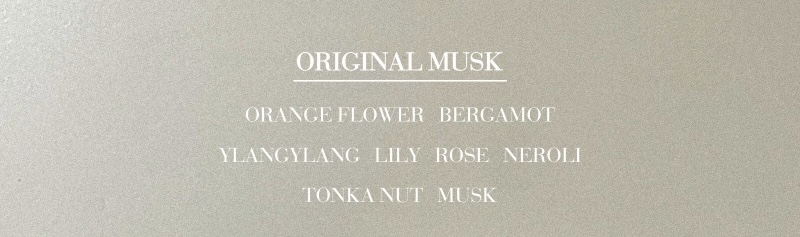
사용된 영문 폰트 알고싶어요
https://developer.apple.com/fonts/ 에 있는 NEWYORK인 거 같습니다! 애플에서 배포하는 무료폰트입니다~
보도니 계열의 아주 일반적인 디자인이라 비슷한건 여러개가 있는데 대부분 유료에요. 무료 보도니도 있으니 한번 살펴 보세요. https://indestructibletype.com/Bodoni.html